在製造業中,品牌溝通從來不只是行銷部門的工作。從企業官網、產品型錄、技術文件,到操作介面、IoT 平台、包裝標示與安全指引,字體都直接影響資訊傳達是否清楚,也影響品牌是否能在全球市場中維持一致、專業且可信賴的形象。
這也是為什麼對製造業而言,字體不只是視覺風格的選擇,而是一項與品牌管理、數位體驗和跨市場溝通密切相關的策略資產。蒙納的字體解決方案,正是協助製造企業在複雜的應用場景中,建立兼顧功能性與品牌價值的字體系統。
TL;DR
- 製造業的字體不只是設計細節,而是影響品牌形象、技術資訊可讀性、數位體驗與全球一致性的關鍵資產。
- 蒙納的字體解決方案可協助製造企業在網站、產品規格、技術文件、App、IoT 平台與多語系市場中,建立更清楚、更一致且更具品牌力的溝通體驗。
- 從參考案例可見,合適的字體策略能幫助製造品牌提升閱讀效率、支援數位轉型、強化國際市場一致性,甚至增加品牌的可見度與記憶度。
為什麼製造業需要完整的字體策略?
製造業的資訊通常專業度高、內容密度高,且常涉及產品性能、操作安全、技術規格與法規要求,因此文字是否容易閱讀、是否能快速被理解,會直接影響溝通品質與使用體驗。當品牌橫跨網站、工業軟體、產品介面與印刷文件時,若缺乏一致的字體策略,品牌呈現與資訊效率都容易受到影響。
從參考案例中可以看見,許多全球工業與科技品牌都選擇以高度清晰、可靠且具現代感的字體作為品牌溝通基礎。這反映出一個重要趨勢:對製造業來說,字體已經不是設計上的附加元素,而是品牌一致性、資訊可讀性與數位體驗的一部分。
應用情境一:建立更鮮明的工業品牌形象
今天的製造品牌不只需要傳達專業與可靠,也需要展現創新能力、現代感,以及更貼近市場與使用者的品牌溫度。字體之所以重要,是因為它往往比文案更早被感知,會先一步影響受眾對品牌的印象。
例如 Schneider Electric 採用 Arial Rounded,在保有簡潔與易讀特性的同時,以圓角設計降低傳統工業品牌的剛硬感,使整體形象更呼應其人本與永續導向的品牌定位。Nucor 則選擇 FS Industrie,以帶有工業歷史感的無襯線字體,傳遞兼具實用性、現代感與品牌底蘊的視覺語言。
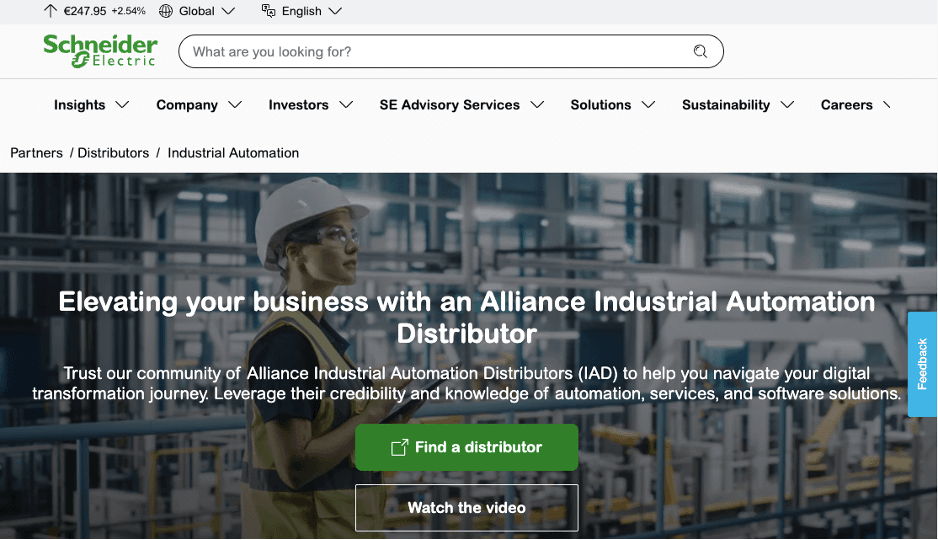
這些案例顯示,字體可以成為製造業品牌升級的重要槓桿。對製造企業而言,當品牌希望從 OEM、技術供應商,進一步走向具辨識度的國際品牌時,字體策略能有效提升品牌的現代性、專業度與整體一致性。
應用情境二:提升技術內容的可讀性與溝通效率
在製造業裡,很多內容不是拿來快速瀏覽,而是需要被正確閱讀、準確理解,甚至作為採購、操作、維修與安全判斷的依據。這使得字體在技術文件、產品規格、使用說明與安全指引中的角色特別關鍵。
Milwaukee Tool 是一個很好的例子。品牌在不同接點依照資訊需求採用合適的字體策略;其中在手冊等實用型閱讀場景中使用 Arial,以其清楚、穩定且高辨識度的特性,幫助使用者更有效率地閱讀操作與技術資訊。STMicroelectronics 則採用 ITC Lubalin Graph 搭配 Arial,讓標題保有品牌特色,同時維持內文的高可讀性。
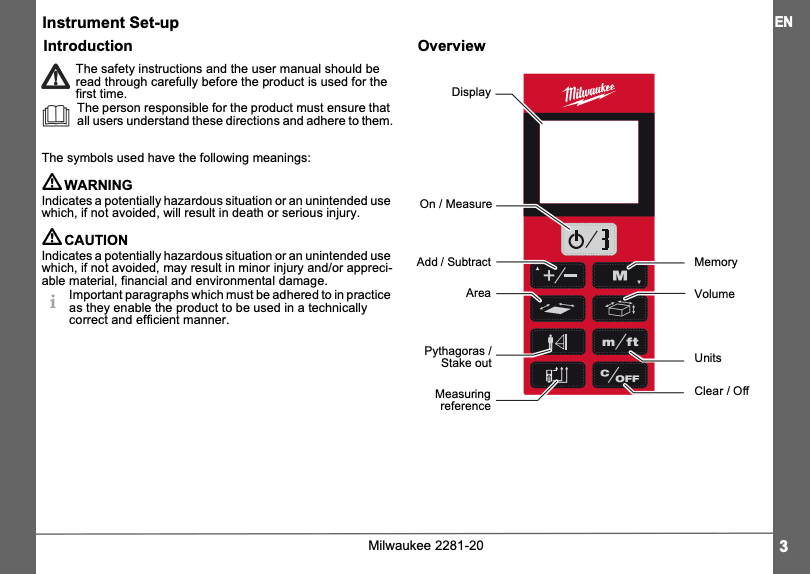
對製造業行銷、產品與設計團隊來說,這代表字體策略其實會直接影響資訊品質。當資訊本身已經足夠複雜,字體系統更應該幫助讀者降低理解門檻,而不是增加閱讀負擔。
應用情境三:支援數位轉型與產品介面體驗
製造業的數位轉型,已經讓品牌接觸點從傳統網站與型錄,延伸到 IoT 平台、監控系統、工業軟體、App 與智慧設備介面。在這些場景中,字體不只關乎視覺美感,更與操作效率、閱讀穩定性與整體使用者體驗密切相關。
Hitachi 的 Lumada 平台在網站中使用 Arial,呼應其作為 IoT 與數位轉型平台所需的實用性、可靠性與跨平台相容性。March Networks 則在網站與 App 中採用 Gotham,利用其高 x-height 與開放字形設計,支援 AI 驅動的數位應用場景,同時傳遞現代、可靠與具科技感的品牌氣質。
這些案例顯示,當製造品牌逐漸把數位平台與智慧服務視為核心競爭力時,字體也成為體驗設計的一部分。這讓字體策略不再只是品牌部門關注的議題,而是與產品、工程、UX 與數位轉型團隊都高度相關。
應用情境四:支援多語系溝通與全球市場一致性
多數製造企業都不是只在單一市場運作,而是需要面對不同地區的客戶、通路夥伴、供應鏈與內部團隊。因此,字體系統不能只在單一語言或單一接點表現良好,而必須能夠支援跨市場、跨平台與多語系的品牌應用。
參考案例中可見,Hitachi、Schneider Electric、ArcelorMittal、ASML 與 STMicroelectronics 等全球品牌,都依賴穩定且可延展的字體選擇,來維持國際市場中的品牌一致性。Transsion 則透過蒙納打造的客製化行動字體 TransSans,以九種字重對應不同 UI 場景,展現字體如何成為多市場數位體驗的一部分。
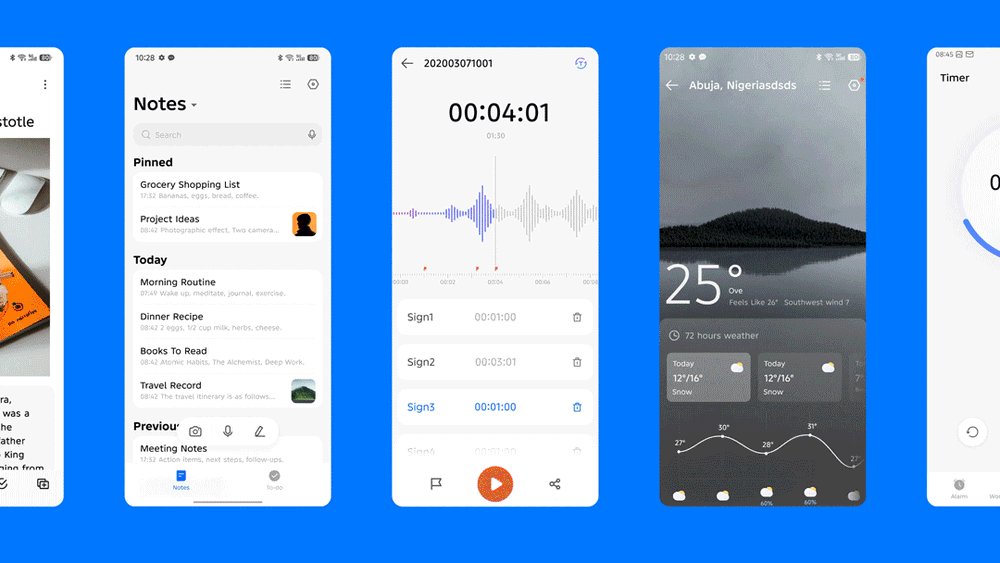
對台灣製造企業來說,這一點尤其重要。許多企業本身具備出口導向與跨國業務結構,因此一套完善的多語系字體解決方案,不只能協助品牌在不同市場維持一致性,也能提升在地化應用時的專業感與完整度。
應用情境五:強化品牌記憶度與差異化
在製造業中,品牌常常圍繞相似的價值主張,例如可靠、創新、品質與永續,因此如何讓訊息更容易被看見、被記得,就成為品牌競爭中的重要課題。字體雖然常被視為基礎元素,但實際上它會對注意力與記憶度產生明顯影響。
ArcelorMittal 的案例就說明了這一點。根據簡報引用的蒙納 Neurons 測試結果,品牌標語改用 Gilroy Bold 後,醒目度提升 12%,在競品中的突出程度提升 5%,顯示字體選擇不只影響整體美感,也可能影響品牌溝通的實際成效。
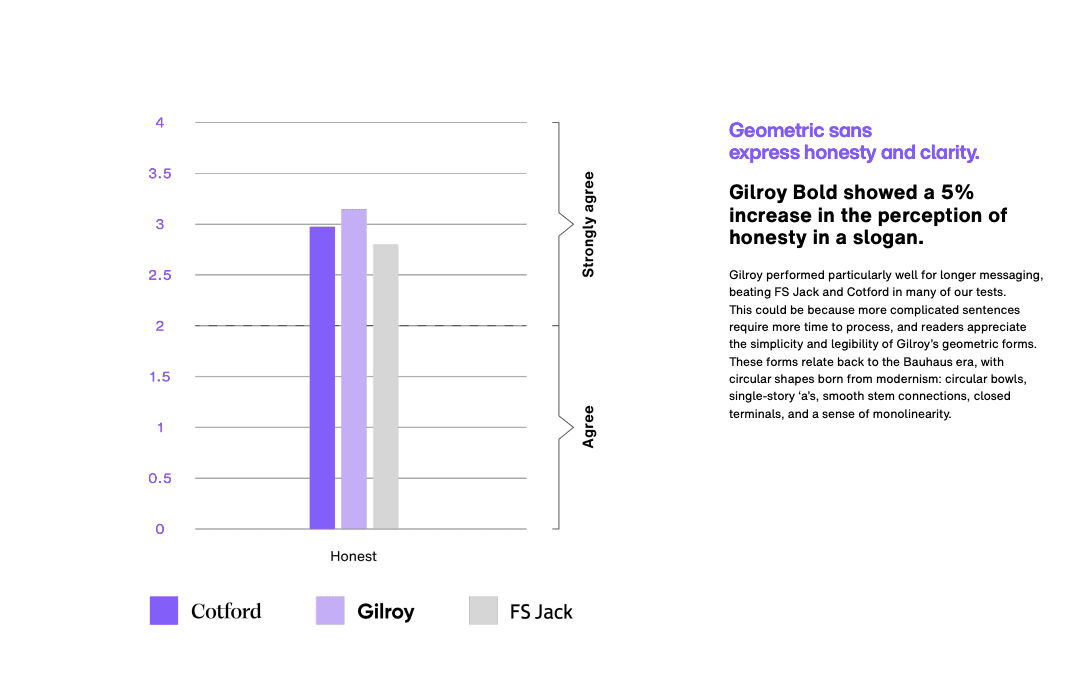
對製造業行銷團隊來說,這具有很高的策略意義。因為品牌表現並不只發生在大型廣告活動中,更發生在網站、展會、產品頁、投資人簡報與日常內容接點裡,而字體正是這些場景中最穩定、最持續發揮作用的品牌元素之一。
製造業選擇字體解決方案時,應關注哪些重點
對製造業而言,真正需要的並不只是單一字體,而是一套能整合品牌溝通、產品資訊與數位體驗的字體系統。從你提供的參考案例來看,企業在評估字體解決方案時,可以特別關注以下幾個面向。
- 是否能提升技術文件、產品規格與安全資訊的可讀性。
- 是否能同時支援網站、App、介面系統與印刷應用。
- 是否能兼顧品牌識別與資訊傳遞效率。
- 是否能滿足多語系與全球市場的一致性需求。
- 是否能在不同螢幕、尺寸與使用情境下維持穩定表現。
- 是否能協助品牌提升辨識度、記憶度與長期價值。
為什麼製造業品牌選擇蒙納
面對品牌升級、數位轉型與全球化布局的多重挑戰,製造業需要的不只是好看的字體,而是一個能真正支援商業目標的字體夥伴。蒙納的價值,在於協助企業從品牌策略、應用場景與使用者體驗出發,建立可以長期擴展的字體系統。
從參考案例可見,蒙納所支援的應用已涵蓋品牌官網、技術文件、App、IoT 平台與客製化數位體驗。這代表字體不再只是創意表現的一部分,而是能夠實際支援品牌一致性、資訊效率與全球市場溝通的關鍵基礎。
結語
在製造業中,字體不只是設計細節,而是影響品牌形象、資訊傳達、數位體驗與國際一致性的核心資產。從技術文件到產品介面,從品牌網站到多語系應用,一套完善的字體解決方案,能幫助企業在每一個接點都傳遞更清楚、更專業且更一致的品牌體驗。
蒙納能協助台灣與全球製造品牌建立兼顧可讀性、品牌力與實際應用效能的字體系統,讓字體真正成為企業成長與品牌競爭力的一部分。對正在推動品牌升級、數位轉型與全球市場布局的製造企業來說,現在正是重新檢視字體策略的最佳時機。